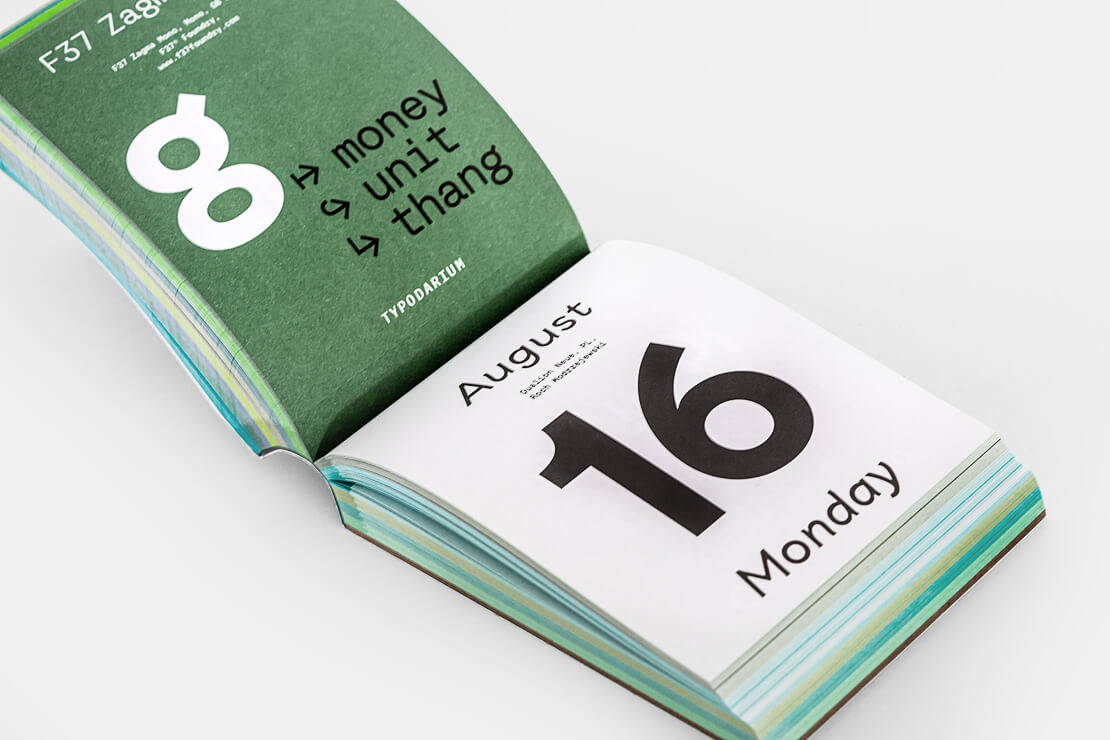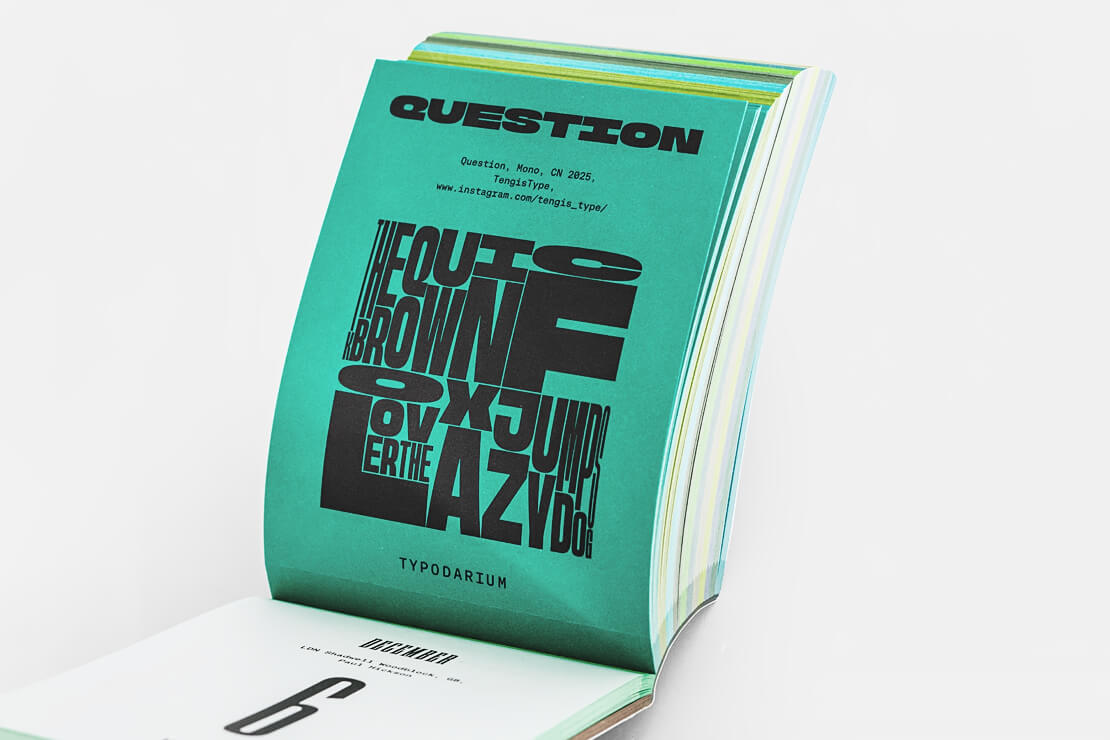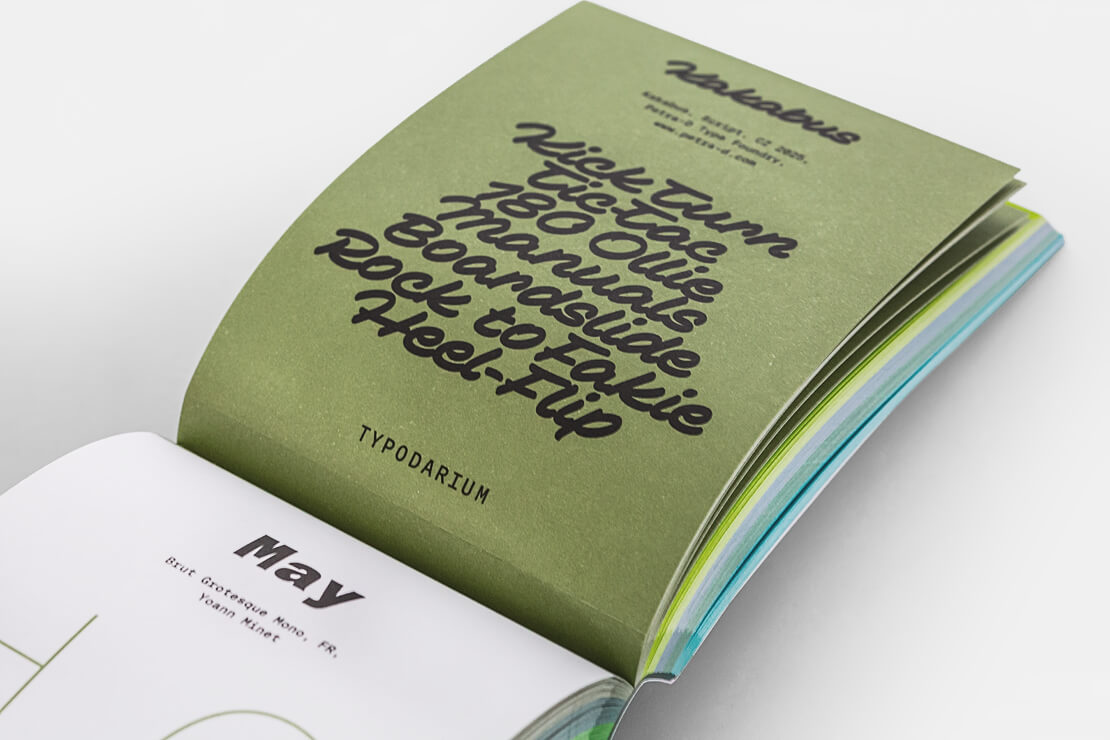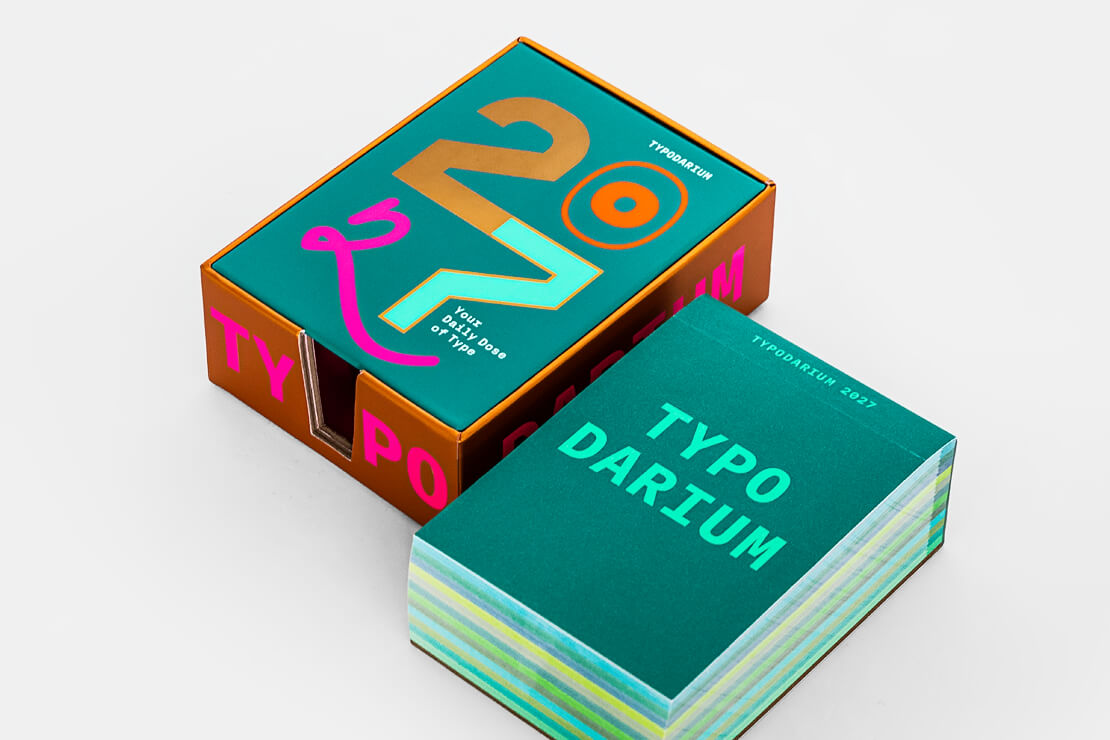
Typodarium 2027 erschienen
Das »Typodarium 2027« ist da und bringt erneut eine kuratierte Auswahl an Schriften direkt auf den Schreibtisch. Die Herausgeber Raban Ruddigkeit und Lars Harmsen präsentieren im typografischen Abreißkalender die Trends im aktuellen Typedesign.
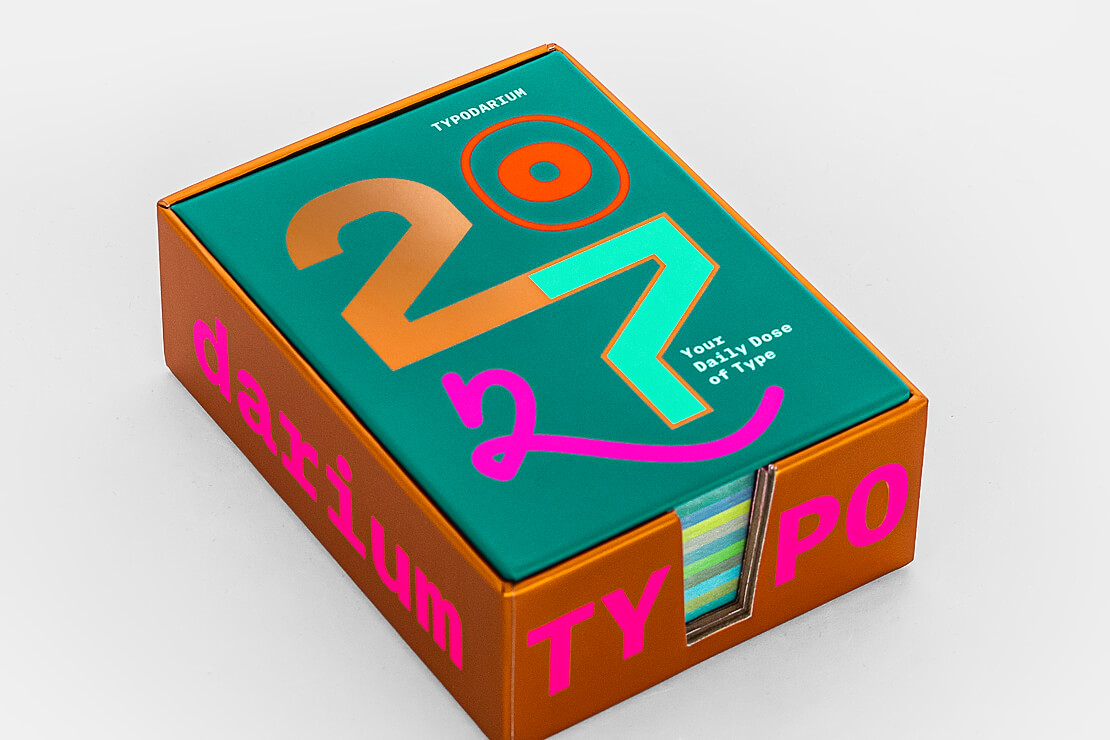
Die Wahl der passenden Schrift ist eine vielfach unterschätzte Komponente visueller Komposition, die jedoch oft unbewusst und kraftvoll kommuniziert. Als Trendradar und Inspirationsquelle bündelt das »Typodarium 2027« daher aktuelle Entwürfe aus der internationalen Type-Szene.
Die Redaktion – bestehend aus Julia Uplegger, Raban Ruddigkeit und Lars Harmsen – scoutet für die jährlich erscheinende Publikation gezielt nach neuen Talenten und aktuellen Arbeiten etablierter Foundries. Jede Kalenderseite rückt dabei eine andere Schrift in den Fokus und liefert auf der Rückseite weiterführende Informationen zu den jeweiligen Designerinnen und Designern sowie den Bezugsquellen.
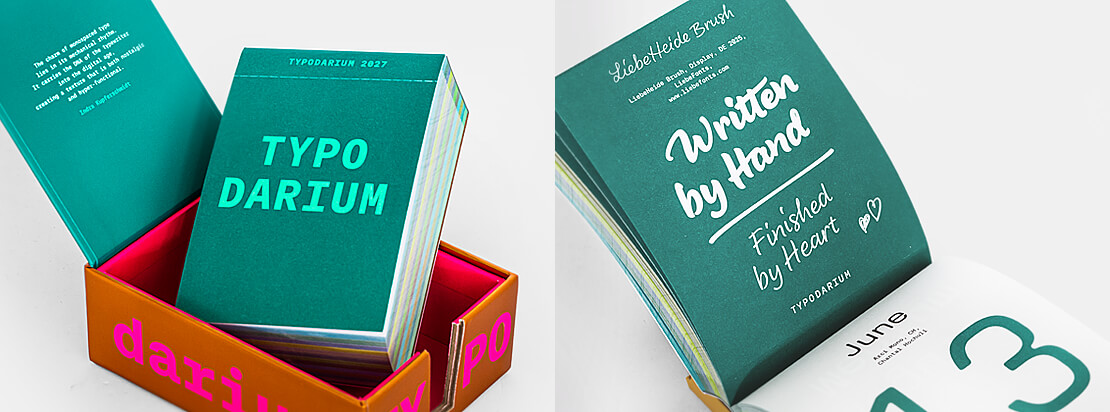
370 Schriften aus 42 Ländern
In der aktuellen Ausgabe versammelt der Kalender 370 frische Fonts von 386 Kreativen und Foundries aus insgesamt 42 Ländern. Wie gewohnt rücken die Sonntage einen bestimmten Meta-Trend in den Fokus: Für das Jahr 2027 liegt der Schwerpunkt auf angesagten Monospace-Schriften. Hierbei zeigt sich, wie Gestalterinnen und Gestalter aus aller Welt den Retro-Charme der Schreibmaschine mit zeitgenössischer Ästhetik mischen.
Format und Ausstattung
Das handliche Format von 8,5 × 12 cm bleibt auch für die 2027er Ausgabe bestehen. Der Block umfasst 384 beidseitig bedruckte Tagesblätter in zwölf unterschiedlichen Farben. Verpackt ist der Abreißkalender in einer soliden Sammelbox, die in drei Sonderfarben bedruckt und mit bronzefarbenen Details veredelt wurde. So lassen sich die abgerissenen Seiten auch nach Ablauf des Tages als kompakter Schriftkatalog archivieren.